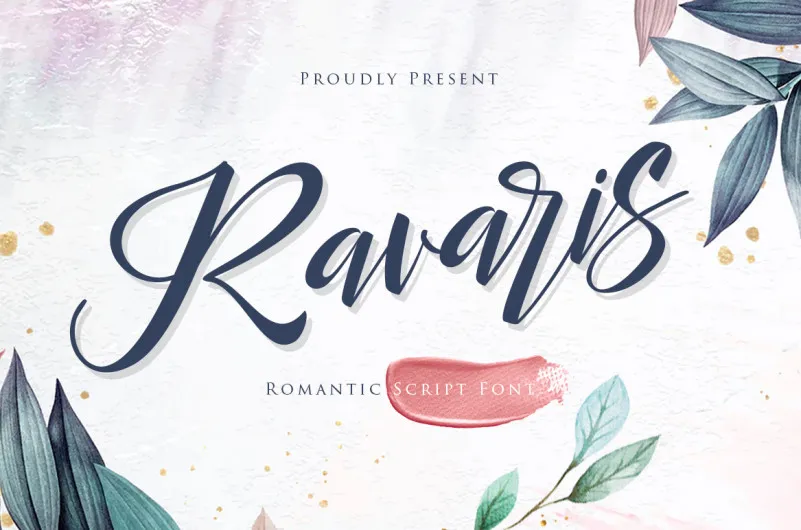
Descubra a sofisticação e a autenticidade que Ravaris Script Font pode adicionar aos seus projetos design. Inspirado pela sua escrita meticulosa com curvas suaves, esta fonte é perfeita para dar um toque elegante e único à sua tipografia, seja em projetos de letras ou marca. Com uma grande gama de letras maiúsculas e minúsculas, pontuação e números, ela oferece suporte multilíngue. Além disso, o designer agniardi incluiu uma ampla variedade de caracteres especiais para que você possa criar cartões de casamento ou molduras atraentes para sua casa. É perfeito para qualquer projeto gráfico, desde letras decorativas até capas de livros e materiais de escritório. Ou simplesmente use-a em suas marcas, revistas, embalagens e mais. A Ravaris Script Font da agniardi é uma ferramenta versátil que pode ajudar você a dar um toque autêntico à sua marca.